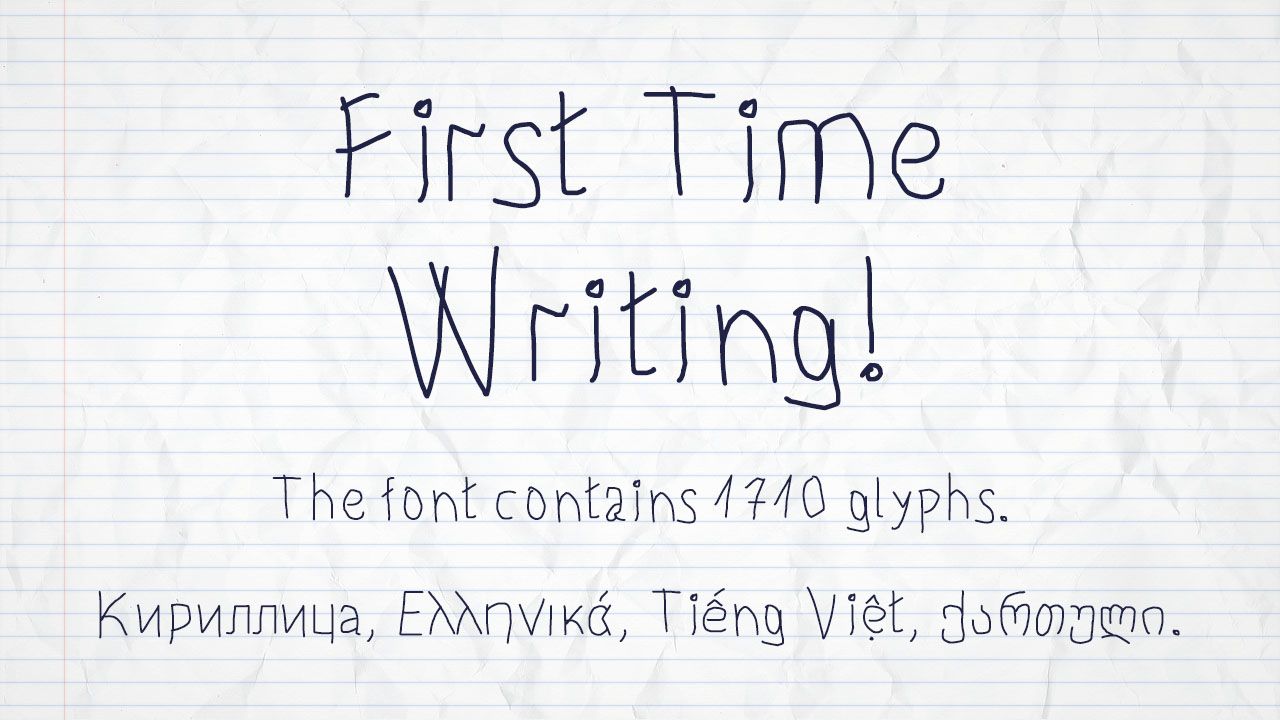
Шрифт «FirstTimeWriting» 1.25
GGBotNet выложил для свободного скачивания обновлённый до версии 1.25 шрифт «FirstTimeWriting». Теперь он содержит 1 стиль и 1710 символов для 103 языков. Визуально он базируется на наблюдении за рукописями учеников в начальной школе. Следовательно, хорошо подходит для детских игр или для стилизации игрового текста под детские записи.